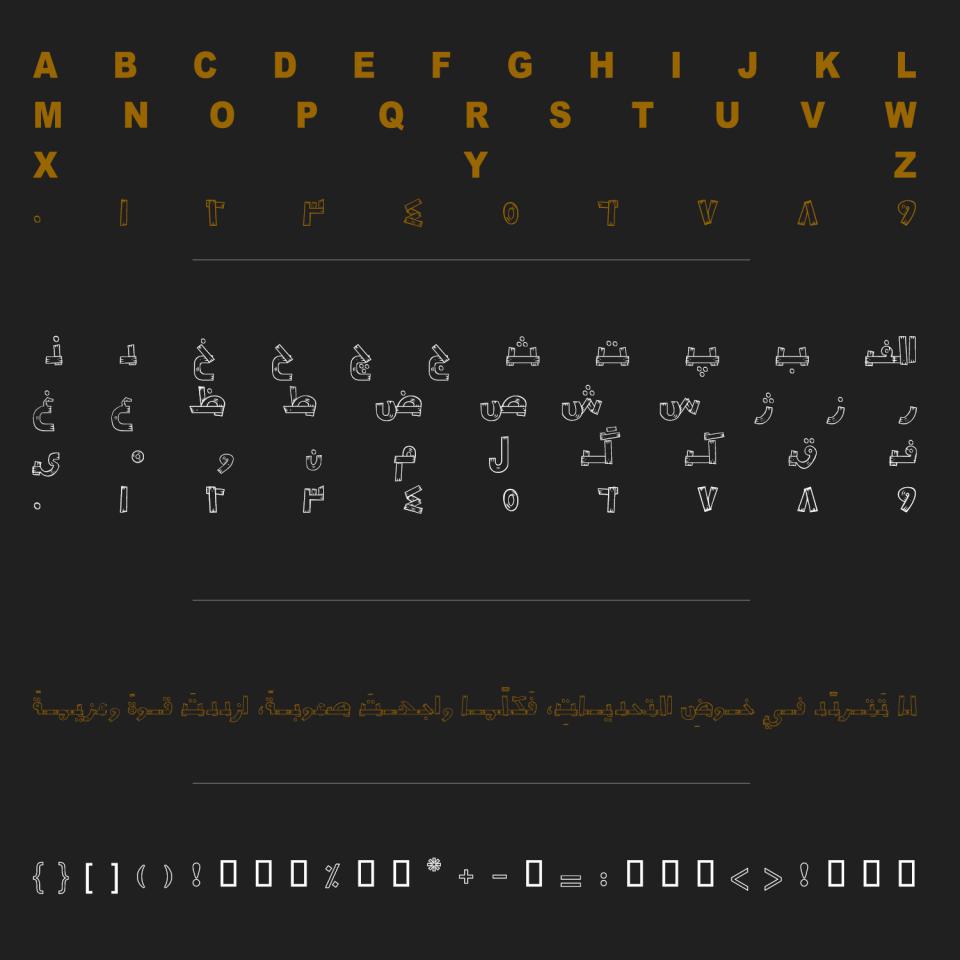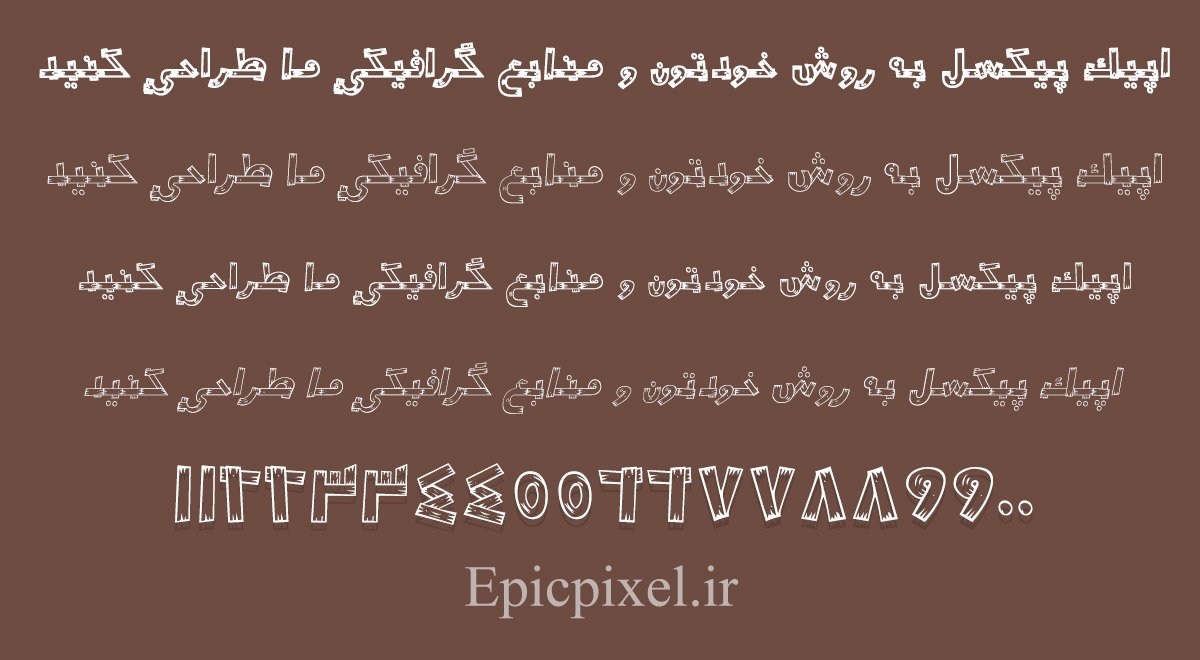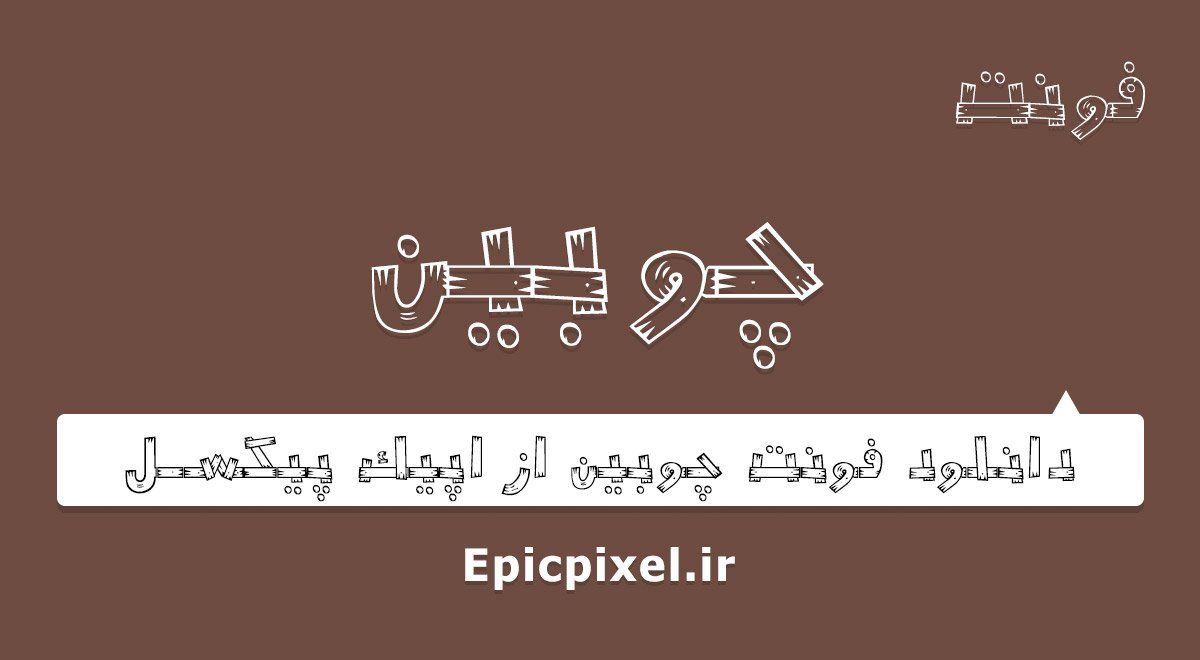
2 فونت چوبین فارسی
فونت چوبین فارسی، با ظاهری خاص و متفاوت، حس گرما و صمیمیت را به نوشته های شما می بخشد. این فونت با خطوط نرم و گرد خود، خوانایی بالایی دارد و در عین حال، حسی نوستالژیک و چوبی را القا می کند. اگر به دنبال فونتی هستید که در طراحی های خود، فضایی دوستانه و طبیعی ایجاد کنید، فونت چوبین انتخاب مناسبی است.
این فونت به خوبی در عناوین، لوگوها، کارت های تبریک و طرح های مرتبط با طبیعت و صنایع دستی به کار می رود. با وجود ظاهر خاص، فونت چوبین در اندازه های مختلف خوانایی خود را حفظ می کند و برای استفاده در متن های کوتاه و بلند مناسب است. با این حال، به دلیل طراحی خاص، شاید برای متن های بسیار طولانی و رسمی، انتخاب ایده آلی نباشد.